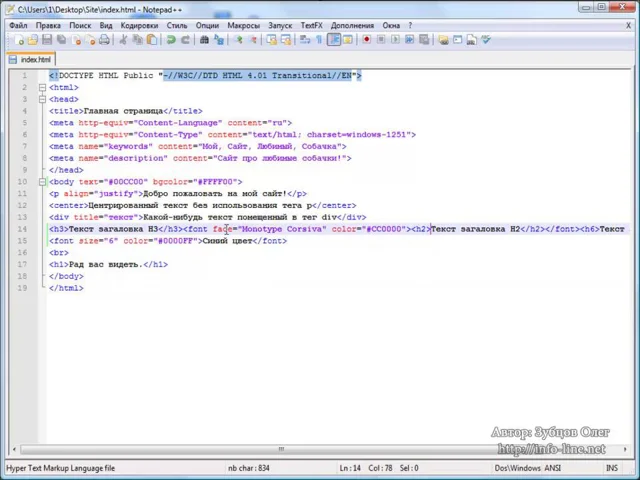
Идеи и советы о том, как сделать ваш текст более выразительным с помощью выделенного шрифта
Выделенный шрифт может придать особую яркость и акцент вашему тексту. В этой статье вы найдете полезные советы и идеи о том, как сделать выделенный шрифт и настроить его в соответствии с вашими потребностями.
Выберите подходящий выделенный шрифт: экспериментируйте с разными шрифтами, чтобы найти тот, который будет наилучшим образом выделять ваш текст.
Используйте жирный шрифт для максимального выделения: жирный шрифт подчеркивает важность вашего текста и делает его более заметным.
Экспериментируйте с размером шрифта: увеличение размера шрифта может помочь сделать ваш текст более выразительным и привлекательным.